世はまさにサバ缶時代。
蒸し暑かった夏が嘘のように肌寒さが訪れた平成最後の秋。
日本では、現在、空前絶後のサバ缶ブームが起きているようだ。
そのブームを全く体感していなかった訳だが、サバ缶の生産量が2016年にツナ缶を凌ぎ、2017年には売上高も抜いてしまった。
水産加工食品メーカーのマルハニチロでは、ロングセラーのサバ缶「月花」シリーズの2017年10月から半年間の売上が2016年同期に比べ157%に増加、サバ缶が品薄状態が続き、サバ缶を求めるサバイバル状態らしい…。
いや、別にダジャレを放ったつもりではないので、きっと誰もこのテキストを裁かんとしないだろう。
現在のサバ缶ブームは女性層を取り込んだ事による事が多いそうだ。
酒のお供はサバ!とサバサバと回答する女性ならともかく、それまでおっさんの酒のお供的な存在だったサバ缶が、女性層を取り込んだ理由が「サバ缶ダイエットによい説」。サバ缶に豊富に含まれている成分であるEPAが痩せるホルモン、「GLP―1」を出す細胞を刺激するという事からサバ缶が女性に認知されたそうだ。
元気があればサバも捌ける!岩手県産株式会社が販売するオサレな「Ça va(サヴァ)缶」
「Ça va(サヴァ)缶」は、「(一社)東の食の会」と岩手県釜石市に工場を持つ「岩手缶詰(株)」と「岩手県産(株)」により、東日本大震災で衰退した被災地三陸からオリジナルブランドの加工品を発信しようと国産サバを使用したオリジナルの洋風缶詰として誕生したそうだ。「Ça va?(サヴァ)?」はフランス語で「元気ですか?」という意味で、岩手県から全国へ向けて声をかけるイメージで名づけられた。
鯖をさばくのが面倒な方にも缶詰はオススメだ。
フランス語「Ça va?」を「金剛黒体 ラテン語」で組んでみた。
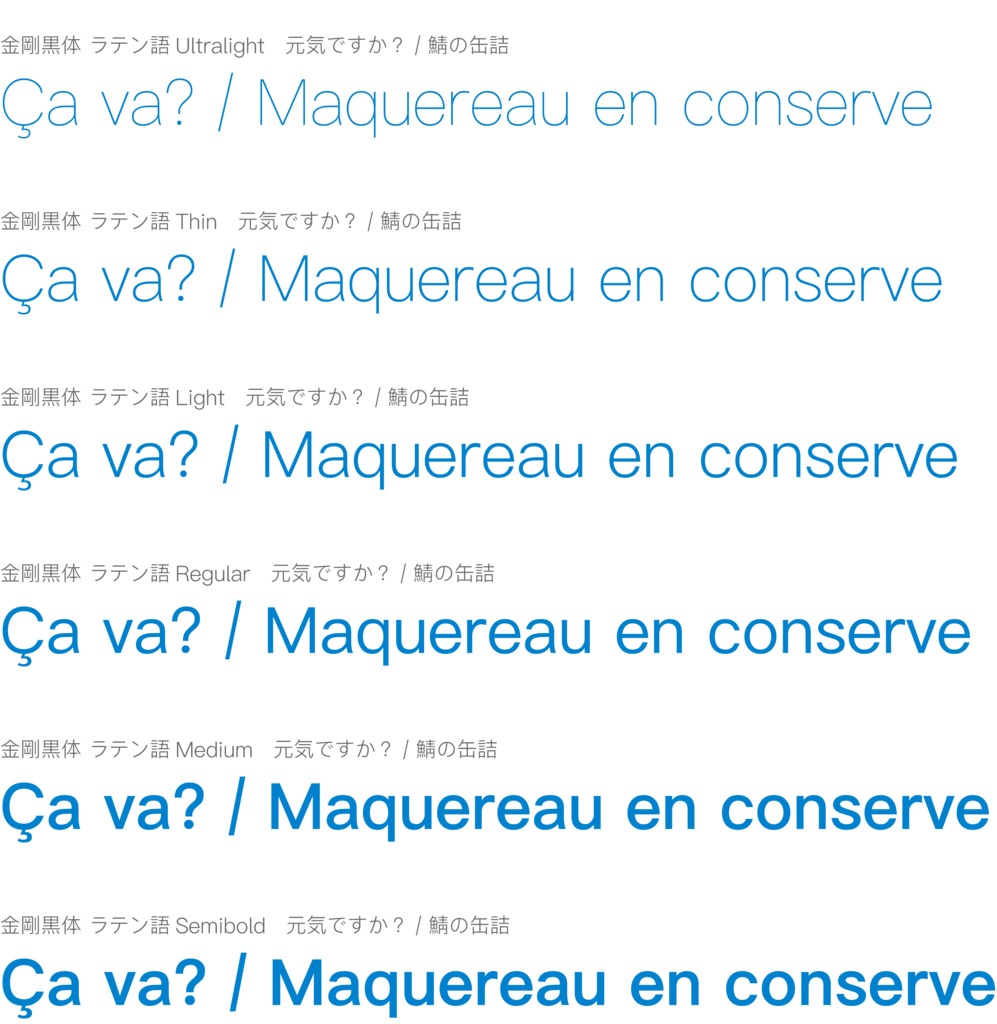
「金剛黒体 ラテン語」は、フランスやドイツなど欧米諸国など様々な国のラテンアルファベット137言語に対応。
シンプルでモダンなスタイルを軸に、全体的にすっきりと洗練されたデザインで、液晶向けにふところを広げることで視認性を高めているほか、フォントの太さを均一にすることでデザイン全体に統一感を持たせ、読み心地を向上させた。